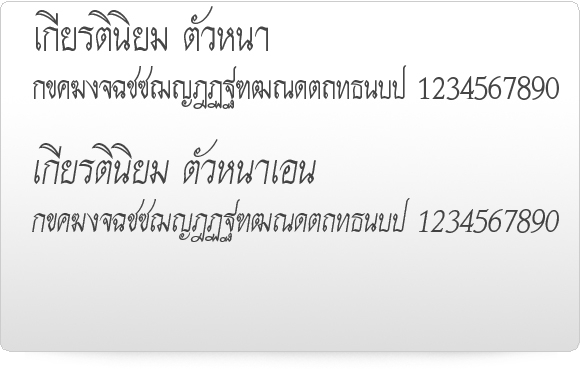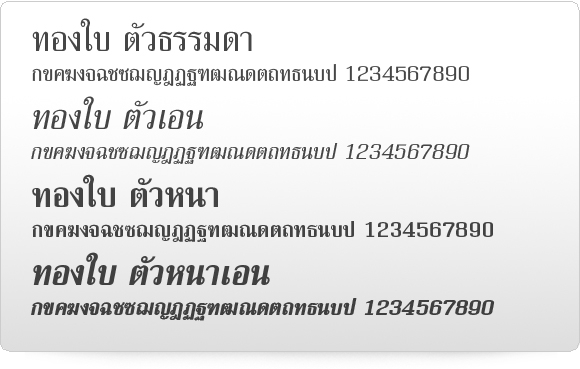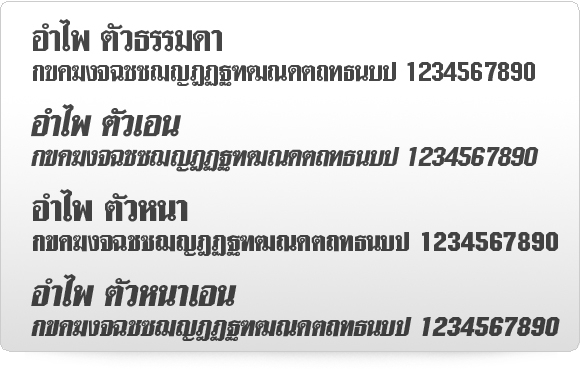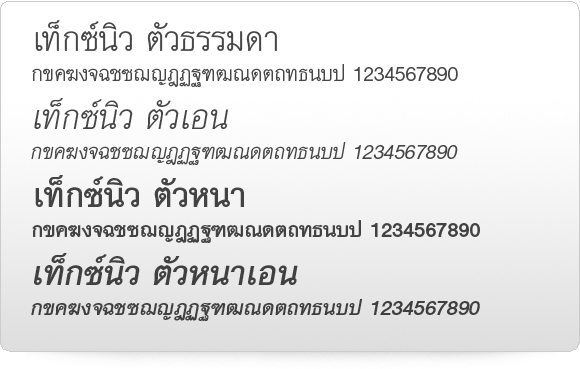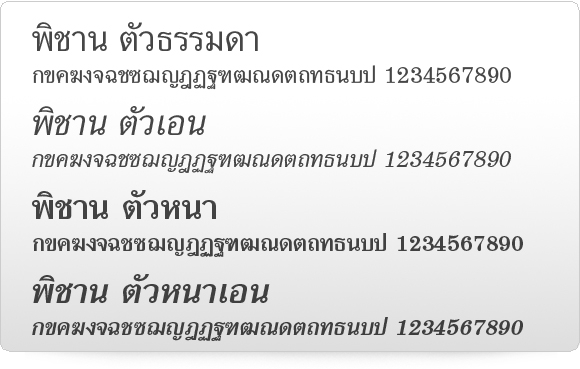
วิเคราะห์ วิจารณ์ PSL5 อย่างเบาๆ
ส่วนนี้ คือ เบื่อมากกกกกกกกก ไม่ขอวิจารณ์ใดใด
พูดได้แค่ เหล้าเก่า ขวดใหม่ วินเทจ
เหมาะกับ หนังสือพิมพ์ จริงๆ  :02: :02: :02:
สวยครับ แต่ผมไม่ค่อยนิยมแนวนี้เท่าไร
Font PSL มีจุดอ่อนหลายอย่าง ไม่ทราบแก้หรือยัง
ตัวโรมันที่มีเครื่องหมาย accent จัดมาให้ไม่สมบูรณ์
é è ë ê ç ........ etc.
Ligature fi fl ไม่ทำ Glyphs ให้โปรแกรมที่เปิดฟังก์ชั่นนี้
เวลาเราพิมพ์ คำที่มี fi fl จะหายไปเลย ????
ไม่จัด feature โอเพ่นไทป์พื้นฐานอันจำเป็นมาให้
Ligature ตัวโรมัน และ ของไทย (นอกจาก ญุ ฐุ ไรพวกนี้) /
Small Cap / เปลี่ยนเลขอารบิกเป็นไทย / เศษส่วน เลขยก เลขห้อย
fi fl ไม่น่ามีปัญหากับ PSLpro ครับ
ก่อนหน้าที่ PSL เขาจะปล่อยชุดโปรมีตัวเถื่อนออกมาเกลื่อน internet (พวก x) อันนั้นไม่ใช่ของแท้นะครับ หรือผมเข้าใจอะไรผิด
มองไปมองมา นึกว่า โนว์ ของท่านเอก คิดว่าคงจะได้แรงบันดาลใจการขึ้นรูปอักษรไทยมาจาก Know